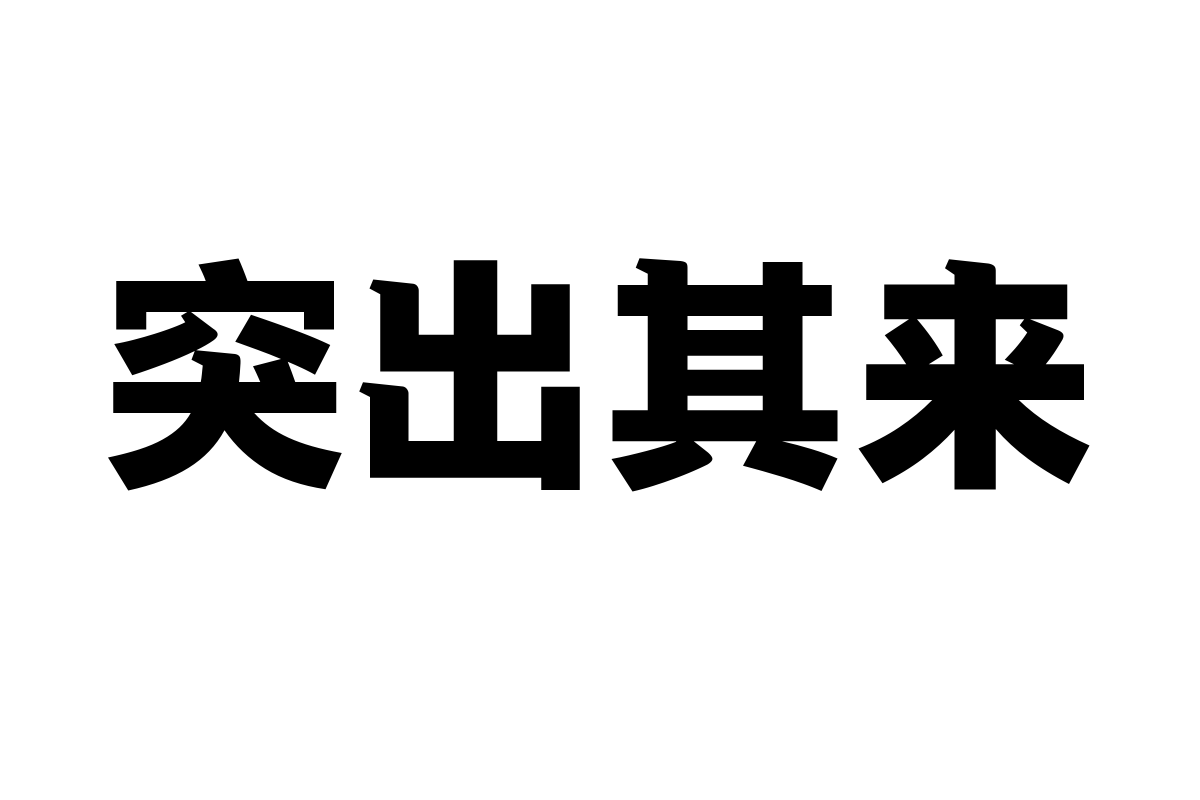
汉仪铁线黑-85是一款专为商业用途设计的字体,具有简洁、现代的设计风格,适用于多种场合如标志、导视、广告等。该字体由汉仪字库提供,并附带详细的使用协议,确保合法合规地使用。
汉仪铁线黑-85简字体风格国际化、简约时尚,适合用于各种书刊、画册和包装设计中。其线条粗壮而端正,整体效果出色,且易于阅读,适合用于海报、品牌标志等设计。该字体广泛应用于广告设计、宣传海报、PPT演示以及影视制作等领域,是设计师们常用的字体之一。
总的来说,汉仪铁线黑-85简字体以其独特的设计风格和广泛的应用场景,为各类设计工作提供了丰富的选择。无论是个人还是商业用途,都能在汉仪字库中找到合适的解决方案。